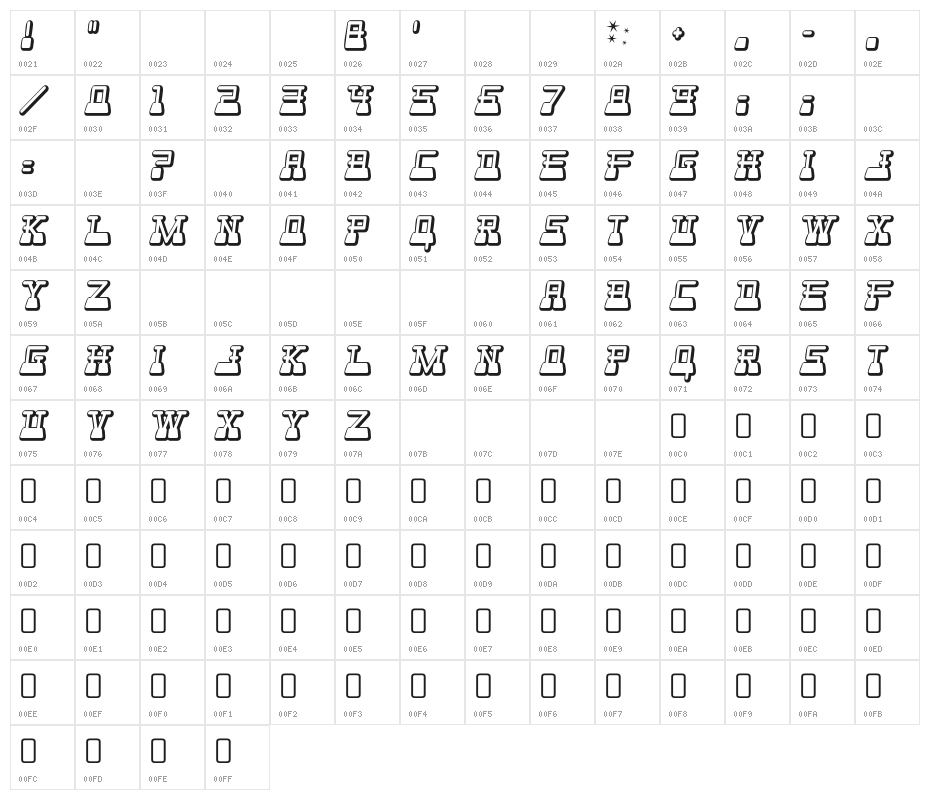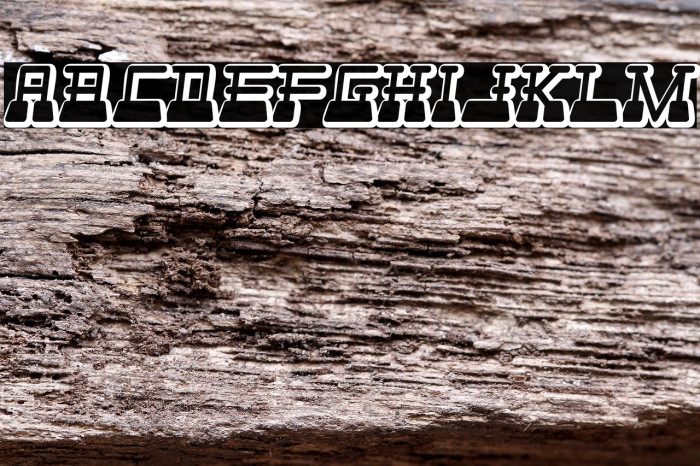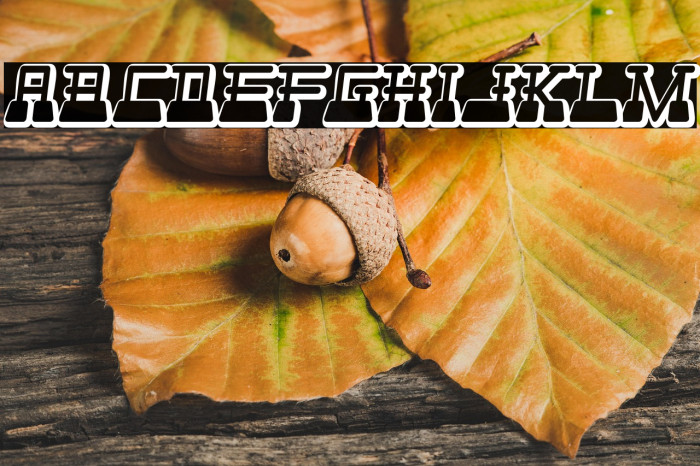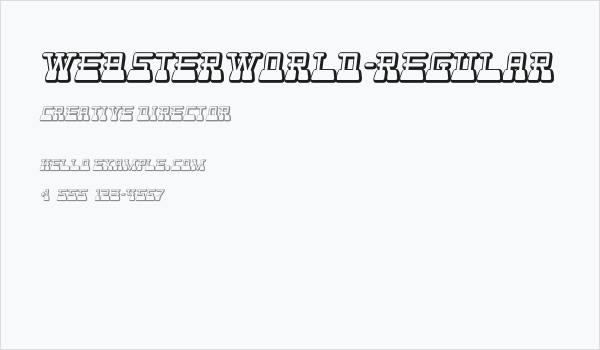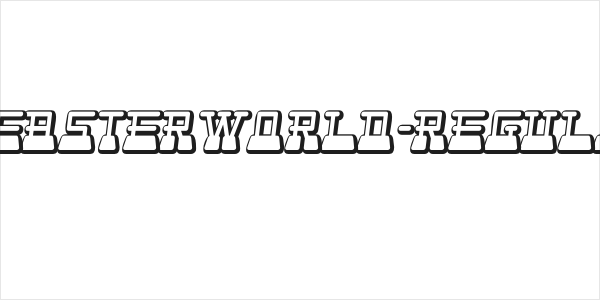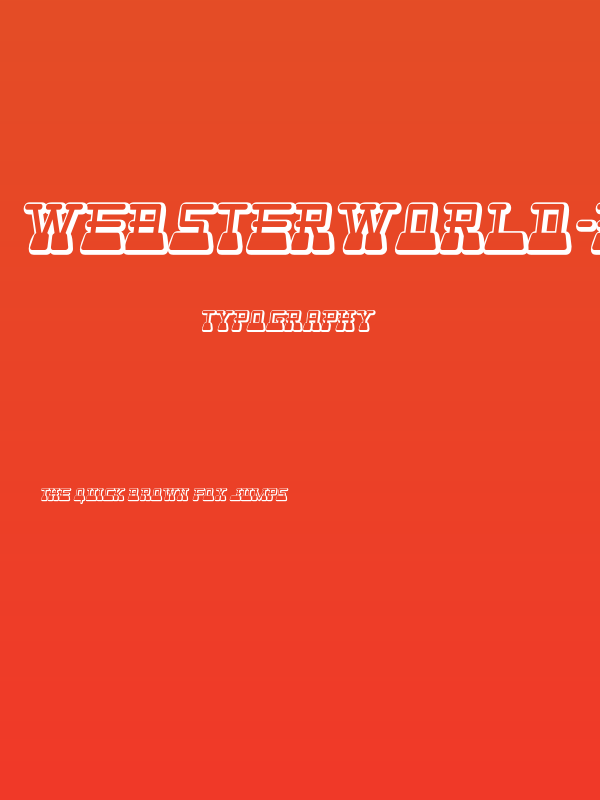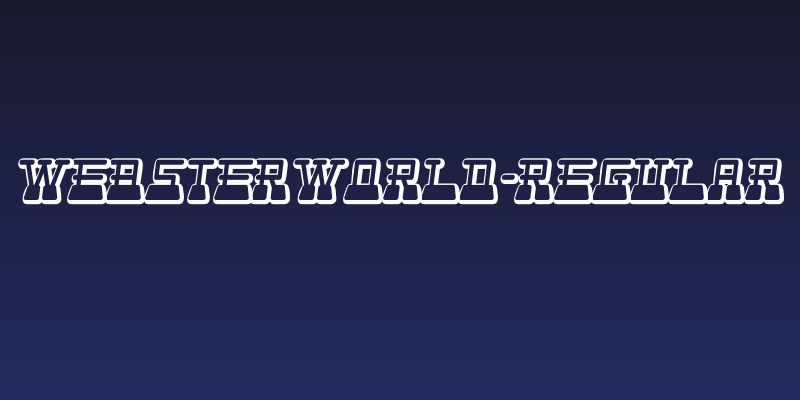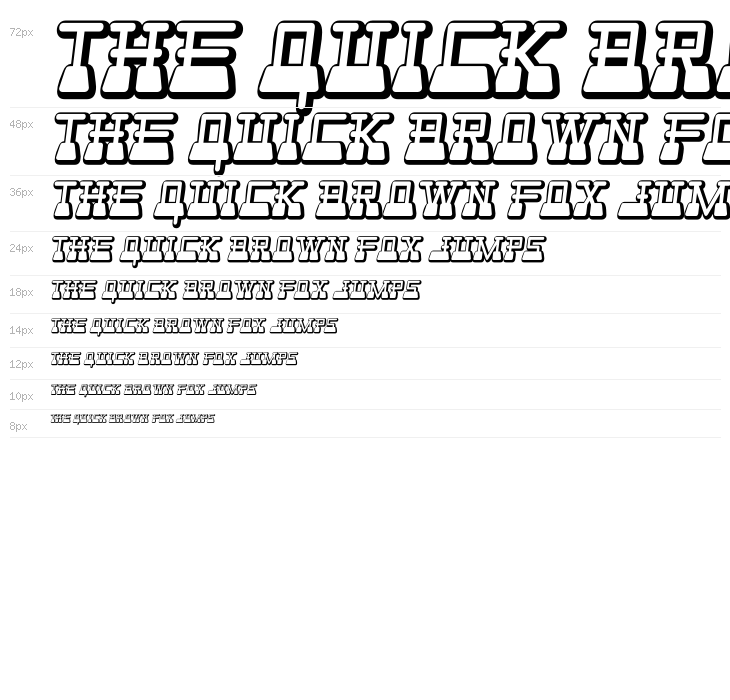
WebsterWorld-Regular Font
✎ 3D
| Categorii | 3D |
| Stil general | Retro, Modern |
| Proiecte propuse | Ideal for projects needing a strong visual impact, such as posters, logos, video game titles, or branding materials. |